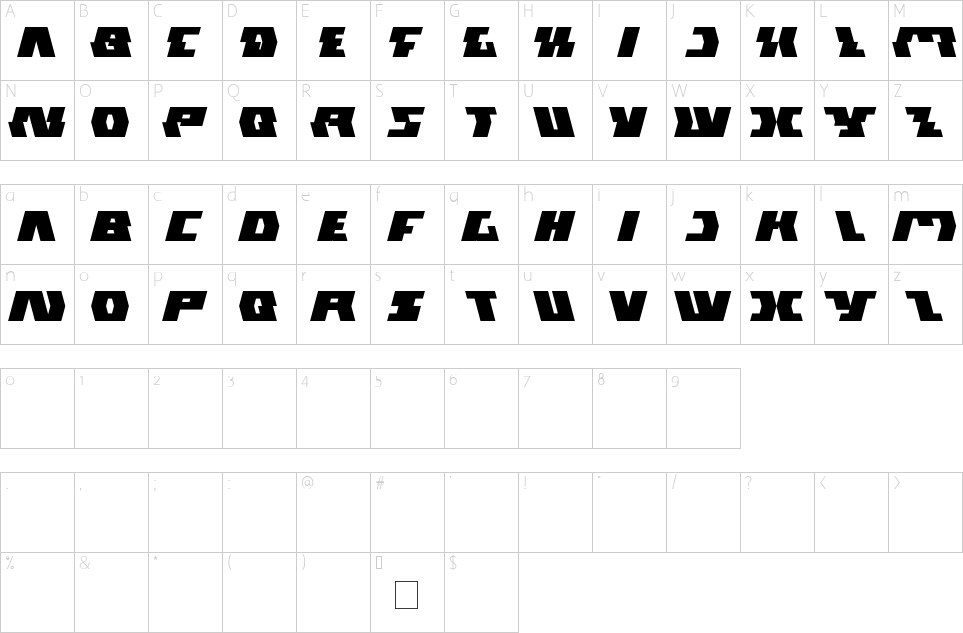
Descubra a adrenalina com a Gladiator Sport Font – uma opção livre para designers que desejam dar vida aos seus projetos visuais. Essa elegante e moderna fonte foi criada por um designer anônimo, mas não perca essa oportunidade de adicionar ao seu portfolio essa poderosa e versátil fonte. Com 2,971 downloads sólidos em poucos meses, é evidente que esta font traz a essência do esporte e da velocidade para qualquer projeto, seja ele editorial ou digital. Seja para estilos de design como logotipos, headings ou texto corpo, a Gladiator Sport Font encaixa-se perfeitamente. Não hesite em explorar esta oferta gratuita e personalize seu próximo trabalho visual com um toque único e excitante da Gladiator Sport.